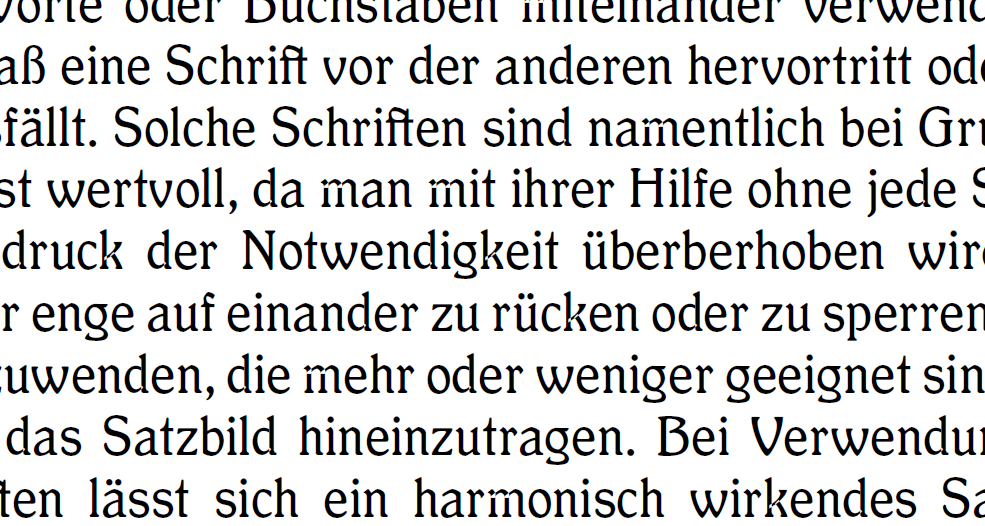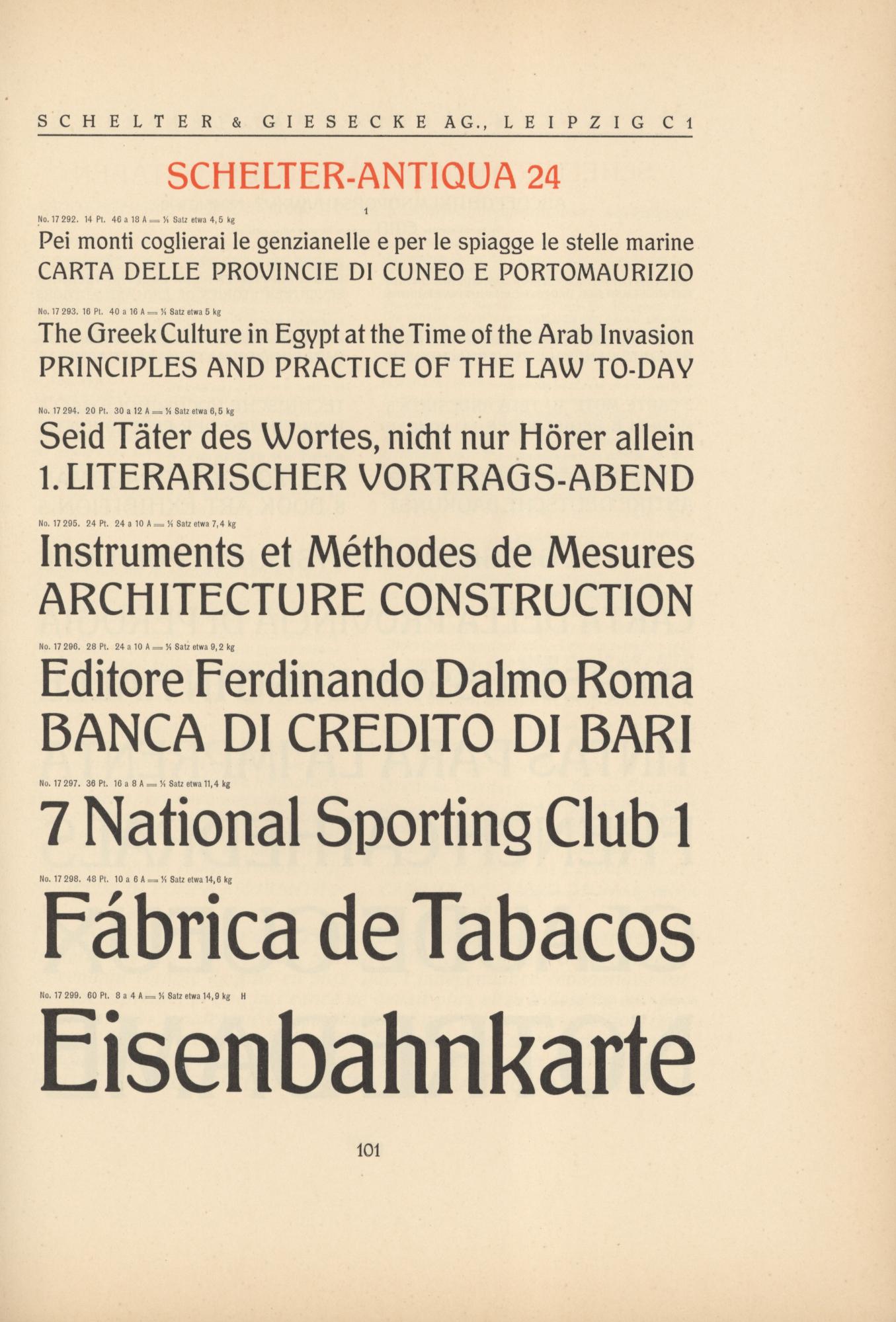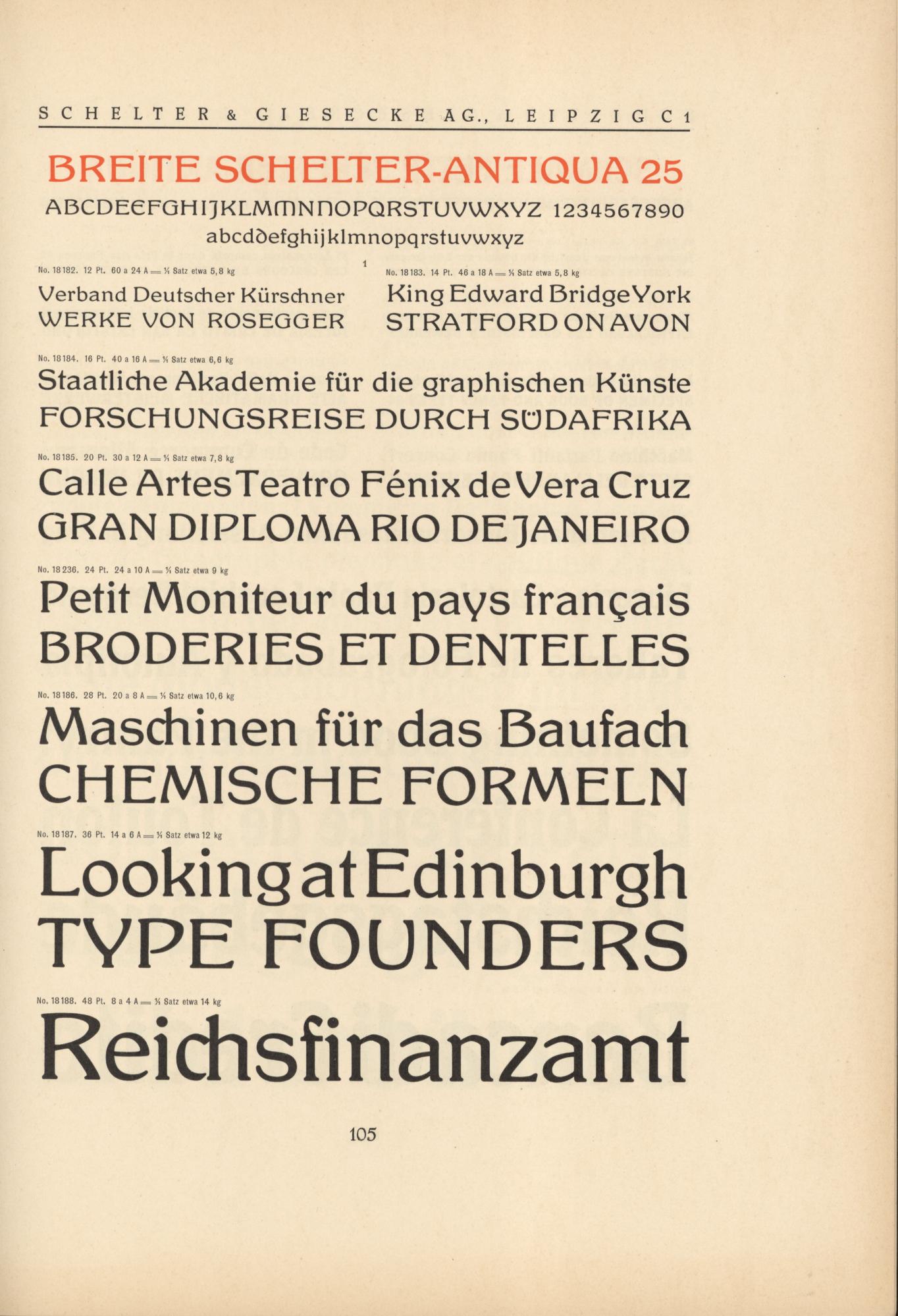
Jugendstil, die Letzte: Schelter Antiqua
Ich empfinde eher die 9 etwas kippelig (nach links geneigt) …
Der »Knoten« in der 8 kommt mit irgendwie versetzt/unterbrochen vor (kann aber auch ein Sehfehler sein).
Ich danke Euch! Ich habe mal überall ein bißchen nachgebessert:i-jbWB39q.png Die Bruchziffern sind auch in der Vorlage höher als die normalen Ziffern. So ganz gefällt mir das nicht, aber ich lasse es erstmal so. Gerade sehe ich, daß zwischen 5 und 9 zuviel Luft ist.
Jetzt finde ich bei der 2 die Linienführung zur unteren Waagerechten etwas schwachbrüstig. Als ob der Oberbau nur noch darauf wartet, sich nach unten zu verbiegen. Aber sie kippelt nicht mehr.
Ich weiß nicht warum, aber die 5 ist schick. Bei der 8 hab ich die Assoziation einer verdrehten Hüfte in der Mitte, die ich aber liebenswert finde.
Die 8 erinnert mich an die Tänzerinnen der 20er und die 5 an diese grüßenden Pinup-Werbemodelle, mit denen die Streitkräfte der USA für Freiwillige geworben haben.
Was man aus Achten alles machen kann! Erinnert mich fast an die Leute, die Buchstaben und Ziffern als Persönlichkeiten auffassen. "Fünf ist frech und vorlaut, aber zwei ist sehr schüchtern" usw. Ich glaube, das ist mit der Synästhesie verwandt?
Aber natürlich hast Du ganz recht mit Deinen Assoziationen!
Fertig?
Mitnichten! Jetzt soll die Kritik erst losgehen, denn bei der Anprobe (ein Wort, das mir besser gefällt als "QA testing") fallen die Ungereimtheiten erst richtig ins Auge. Ich selbst habe in diesem Bild schon ein paar Schnitzer entdeckt; bitte sagt mir, was Ihr hier und in den folgenden Anwendungen findet.
Ich finde die obige nach rechts weit ausladende Serife des L in Lesegrößen irritierend. Wäre das nicht eher etwas für optische Größen?
Es sind ja nun nur wenige Versalien im Text, aber ich denke, dass diese ebenso wie das angemerkte L irgendwie irritieren würden; das S ist ja auch etwas verhaltensauffällig. Allerdings ist dies eben auch keine »normale« Schrift, sondern sie hat eine deutlich stilistische Ausprägung – was würde von der bleiben, passte man die ganzen »Ungereimtheiten« an?
Phoibos, diese Eigenschaften der Schrift stechen sicherlich heraus, aber ich stimme hier Norbert zu, denn diese Dinge abzuschleifen würde die Schrift mit dem schon existierenden Einerlei gleichschalten. So wie ich es sehe, braucht man einen angenehmen Kitzel, wie wenn man als Kind einen losen Zahn hat, und mit der Zunge daran rumdrückt, bis es weh tut – nicht sehr, nur so, daß es Spaß macht 🙂
Mich haben spontan die ungewohnten Breiten der Minuskeln verwundert, z. B. das im Verhältnis zum s und e sehr schmale n und u. Aber noch störender fand ich, dass auch der formale Duktus nicht zusammenpasst: m, n,  r, u, … eher mit »eckigen« Rundungen – a, d, e, s, … hingegen ganz normal. Beides zusammen lässt eine der beiden Gruppen wie Fremdkörper erscheinen. Aber auch das war ja in der Vorlage schon so und soll wohl ebenso  zum »Kitzel« gehören, oder?
Das gehört ganz gewiß dazu, und war jedenfalls Absicht. So beschreiben es zumindest die Schöpfer der Schrift in diesem Artikel, der in der S&G Hauptprobe von 1912 erscheint:
Ob die Sache am Ende erfolgreich war, sei dahingestellt. Ein langes Leben war der Schelter-Antiqua nicht beschert, und das spricht schon mal für sich. Andererseits war sie wohl die Vorlage für die ITC Souvenir, also zumindest "verwertbar".
Optisch und zeitgeschichtlich paßt sie m. E. zu den anderen Schriften; ob sie getrennt davon in einer modernen Anwendung am Platz ist, bezweifle ich.
* Übrigens sträubte sich der Artikel dagegen, von handelsübliche OCR-software gelesen zu werden. Ich habe ihn also kurzerhand meinem Macbook vorgelesen. Erstaunlich, wie gut die Diktierfunktion ist.
Sehr schön. In Acrobat Pro 2020.012.20048 werden einige Glyphen bei den Formüberschneidungen allerdings noch fehlerhaft dargestellt (/k, /m, /d).
Ich weiss noch nicht so recht, was ich vom V halten soll, die übrigen Versalien sind ja so ein büschen von den Gemeinen abgesetzt, das Vo (bei der Kombi ist mir das zuerst aufgefallen, aber auch Ve betrifft es) hingegen wirkt da anders auf mich. Als ob da Kerning reinspielt. Das W hat das nicht, obwohl ich schätze, dass die die gleichen Metriken haben.
Herzlichen Dank! Die der Breiten hatte ich schon, aber da ich irgendwann alle sechs Schnitte machen will, sind Deine Scans ungemein hilfreich!!